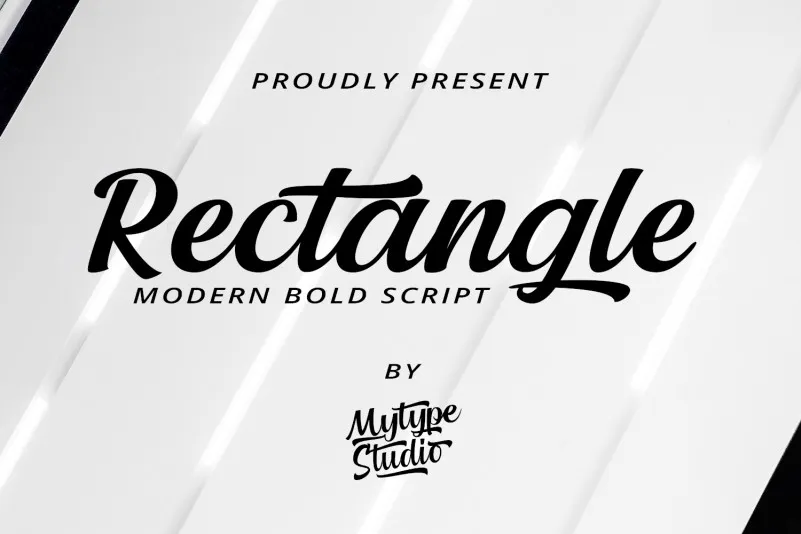
Rectangle Font – Download Grátis
Esta é uma fonte escrita a mão, moderna e forte, projetada para dar um toque elegante aos seus headlines e logotipos. Esta fonte leva os olhos a desfrutar de sua força, confiança e dinamismo, e pode adicionar tons de nostalgia incríveis aos seus designs. Ideal tanto para aplicações publicitárias quanto para elementos visuais no design editorial, esta ‘Rectangle Font’ da categoria Script Fonts traz um toque único à qualquer projeto. Sua criativa natureza vem do designer Icreatype, com este estilo que se destaca pela simplicidade e eficácia na comunicação visual. Experimente essa fonte para adicionar uma camada extra de personalização aos seus trabalhos gráficos.